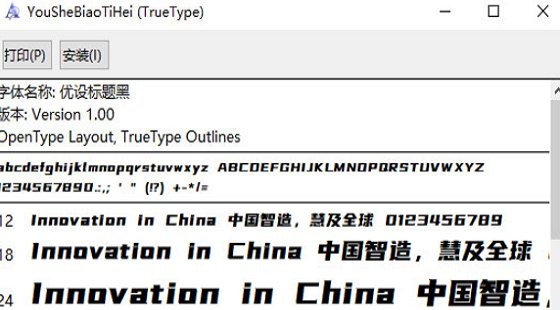
优设标题黑字体为大家提供ttf字体黑体字体等多种免费字体的获取使用,艺术感十足的字体形态大家用起来非常的好看,是款适用于广告设计方面的字体。且操作简单,实用性强,极大地为大家带来更多的选择,欢迎有需要的用户前来下载使用!
※用在各类品牌广告和产品包装设计的标题上,最合适不过
※它以黑体字型为基础,整体字形沉稳,同时采用较大字面和粗壮的笔画来强化力量感。每个字体水平倾斜8°的设计,赋予了字体极强的速度感,为了让字体倾斜后也能保持稳固,设计师将整体字身设定宽扁。而起笔和弯钩上独具匠心的尖角设计,不仅突显了设计的几何感,而且方便后期修改。
2、改字体带有一点倾斜效果,正式感的同时又不是艺术感